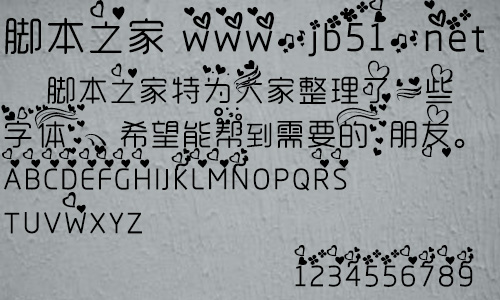
【太陽君】滿天心4字體是一款藝術(shù)卡通字體,這款字體以心形圖案為元素進(jìn)行點(diǎn)綴,看上去十分的可愛,適合應(yīng)用于藝術(shù)設(shè)計(jì)、平面宣傳設(shè)計(jì)、網(wǎng)頁設(shè)計(jì),書法字帖等領(lǐng)域。歡迎需要的朋友前來本站下載使用。